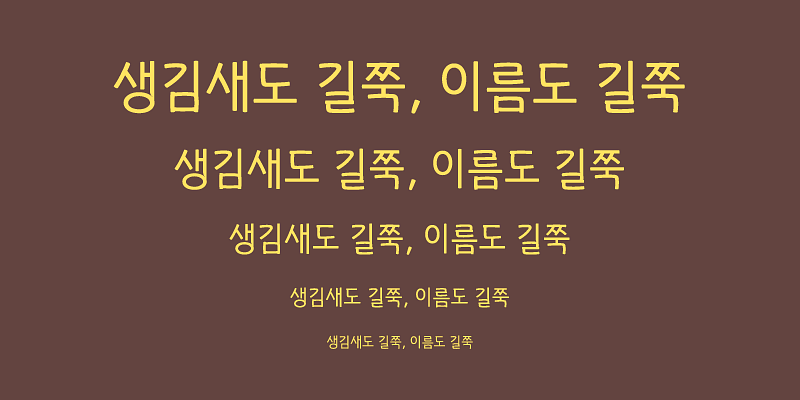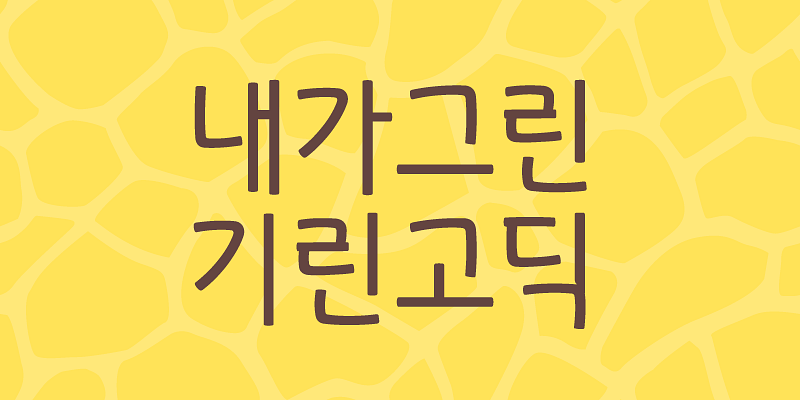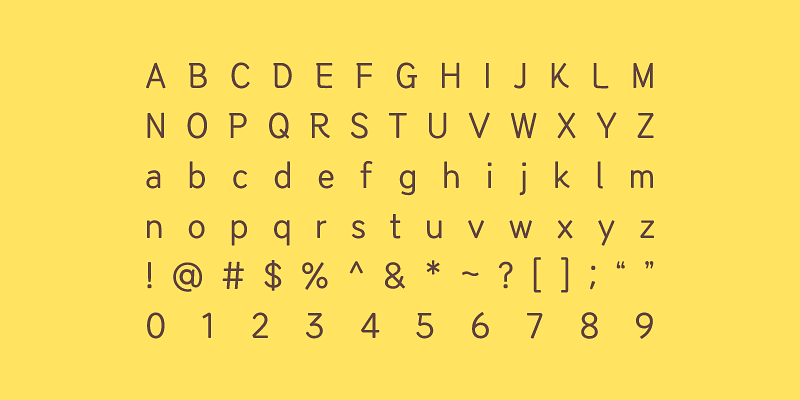
Diese Schrift, die einer großen, robusten Giraffe ähnelt, zeichnet sich durch ein längliches, abgerundetes Design aus. Sie fängt die entspannte Atmosphäre einer warmen, freundlichen Handschrift ein und behält dennoch die elegante Essenz einer serifenlosen Schrift bei. Die langen, klaren Linien der Schrift sind ausgewogen angeordnet und fördern so die einfache Lesbarkeit und klare Erkennbarkeit des Inhalts.